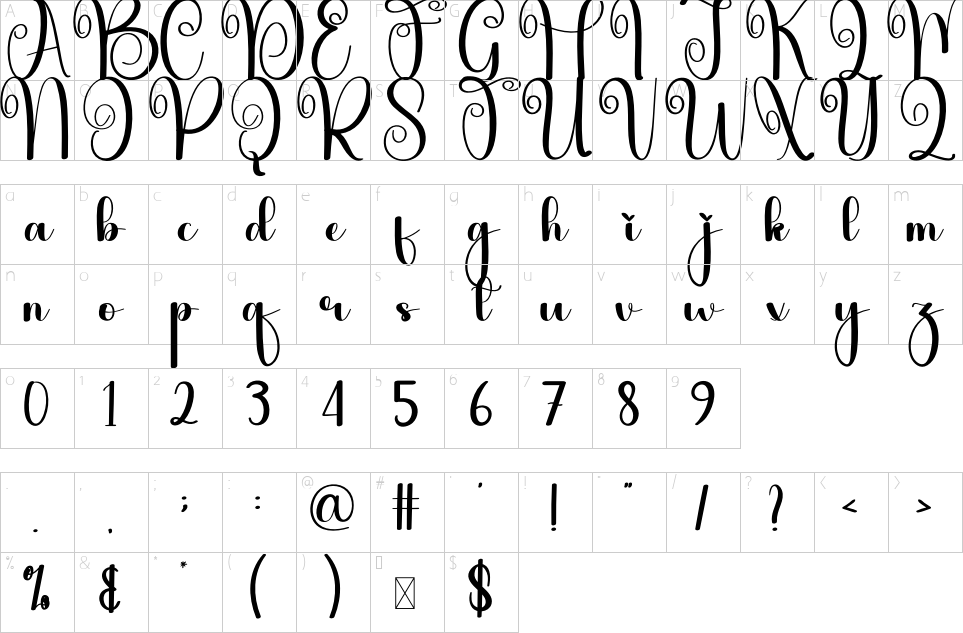
A fonte Samantha é uma opção gratuita e divertida para aqueles que buscam um design elegante e sofisticado para seus projetos digitais. Desenhada pelo designer anônimo scratchones, Samantha oferece uma variedade de opções de estilo, incluindo linhas elegantes e elegantes, que se tornam a escolha perfeita para criar designs profissionais e atraentes. Com seu design minimalista e moderno, a Samantha é uma fonte que encaixa-se perfeitamente em qualquer projeto, desde sites de blogs até documentos de negócios. A fonte Samantha foi descarregada 564 vezes, uma indicação de que ela é popular entre os designers digitais e os amantes da boa fonte. É uma ótima escolha para aqueles que buscam um design moderno e elegante para seus projetos, sem precisar gastar dinheiro. Seja para o seu site pessoal, documentos de trabalho ou até mesmo para seus projetos de design gráfico, Samantha será uma fonte muito apreciada. Descarregue Samantha agora e veja como ela pode se tornar uma parte importante de seus projetos digitais.